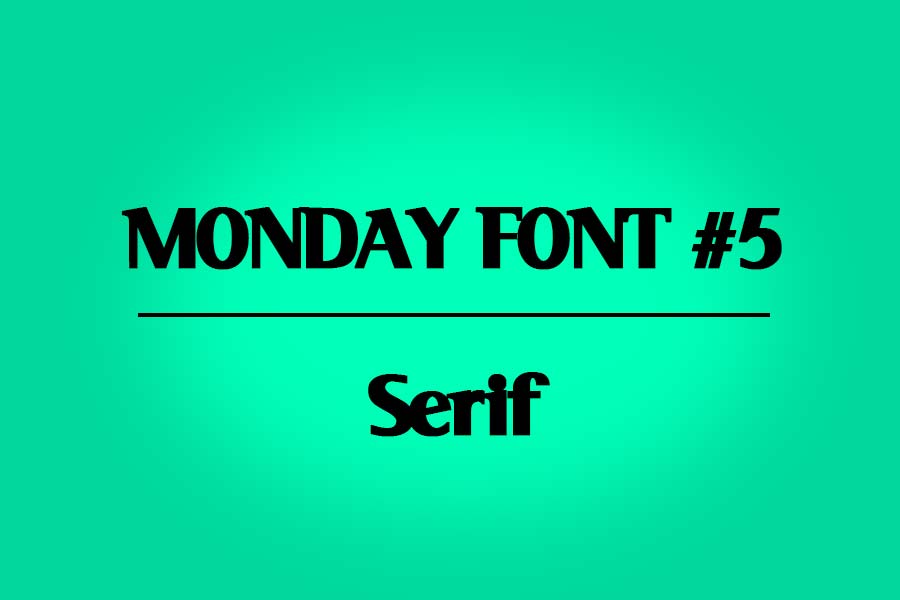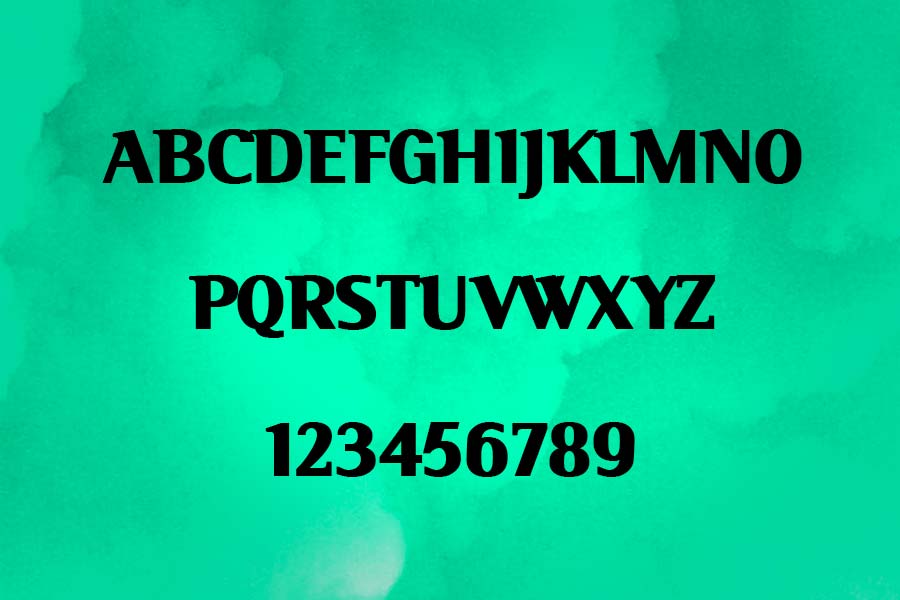
Monday Font llega a su quinta entrega con una nueva fuente tipográfica a recomendar. El turno de hoy es para Serif, una tipografía con serifa “fuerte” y compuesta por varias versiones de la fuente (Bold, italic,…) A disfrutar de ella!